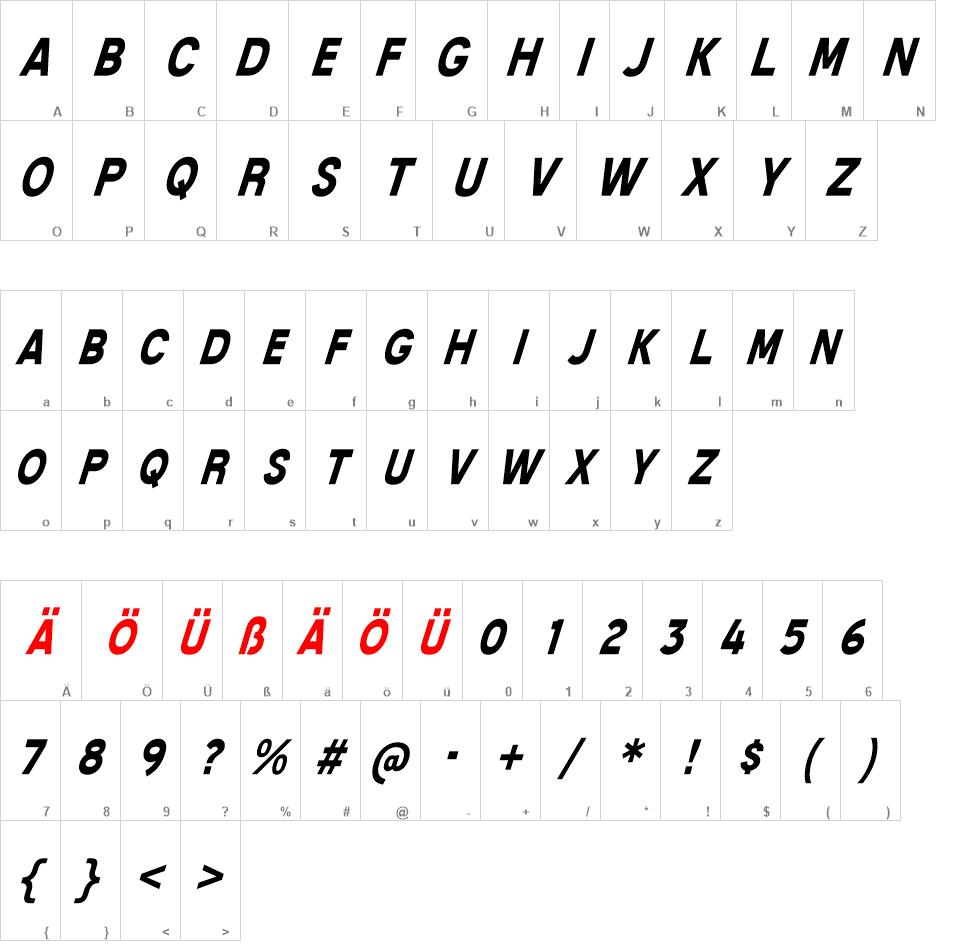
Mixolydian Titling
Mixolydian ist eine technische serifenlose Schrift. Während technische Schriften wie DIN ein europäisches Flair haben, wurde Mixolydian mit einem ausgeprägten amerikanischen Stil erstellt. Ein Teil des visuellen Aspekts wurde vom Standard-Alphabet der US-Bundesautobahn (Highway Gothic) und von architektonischen Entwurfsvorlagen erworben. Der Rhythmus jeder Buchstabenbreite ist bewusst abwegig, um ein nützliches, wissenschaftliches Gefühl zu erzeugen. Die Mixolydian-Familie umfasst sechs Gewichte sowie sechs stark geneigte Schrägbalken. Wenn Sie für Ihr Projekt Kleinbuchstaben benötigen, sehen Sie sich die normale Mixolydian-Familie an.